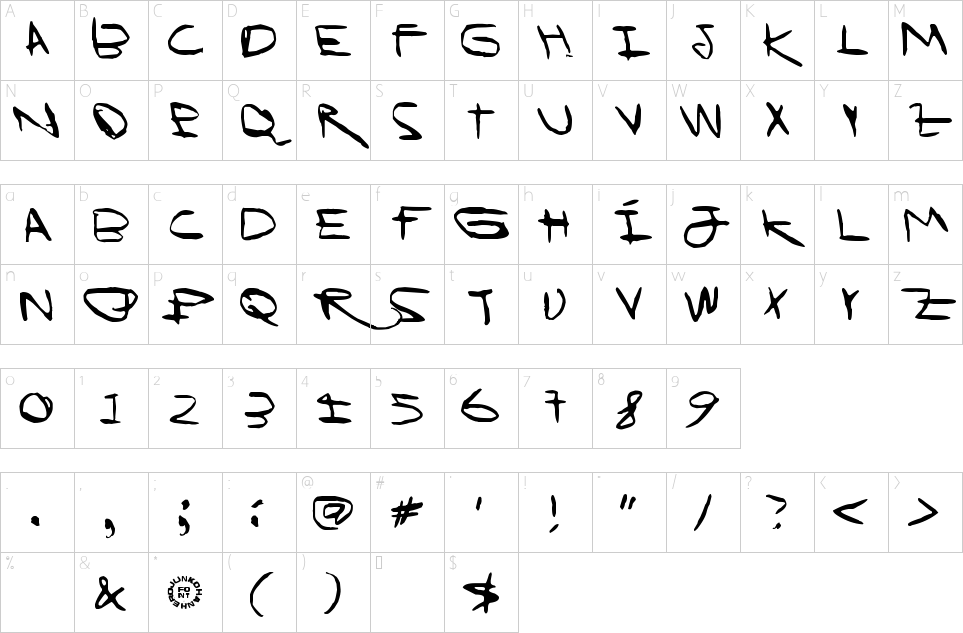
A fonte ‘I Wanna Be Your Dog’ é um design criado por junkohanhero, disponível gratuitamente tanto para Windows quanto para Mac. Esta elegante fonte é ideal para quem busca um toque único em seu design. Ela foi popularizada em um número recorde de 2,013 downloads, demonstrando seu valor e popularidade. Seja para criar um logotipo inovador ou simplesmente para personalizar sua página de blog, esta fonte adocicada certamente encaixará perfeitamente em qualquer projeto. Se você está à procura de algo que dê um toque especial ao seu trabalho, ‘I Wanna Be Your Dog’ será uma ótima opção.